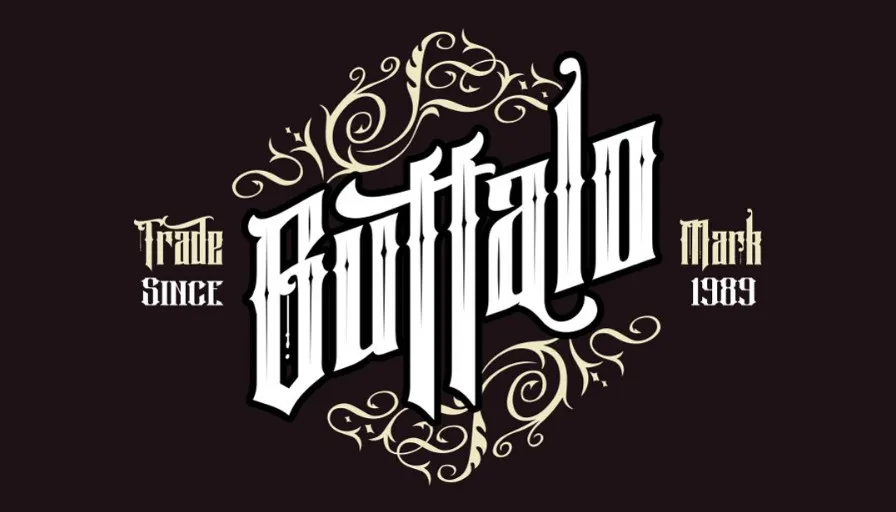
A INKSUN™ nos apresenta Black Oval Typeface, uma seleção ideal para quem procura uma fonte vintage contemporânea. Perfeita para criar design moderno e sofisticado, esta fonte traz elementos do estilo blackletter com toques de revolução vintage. Ideal para trabalhos criativos como panfletos, camisetas, logotipos, rótulos e tudo mais que você precise imprimir ou desenhar digitalmente. Com sua elegância única e sofisticação moderna, Black Oval é uma escolha perfeita para aqueles buscando uma fonte que combinam a modernidade com um toque nostálgico em qualquer projeto de design.